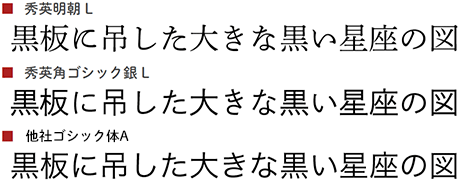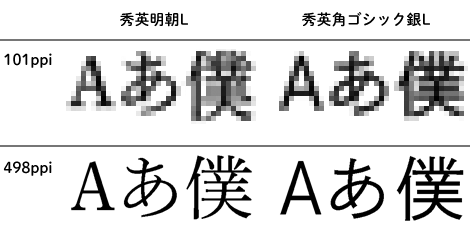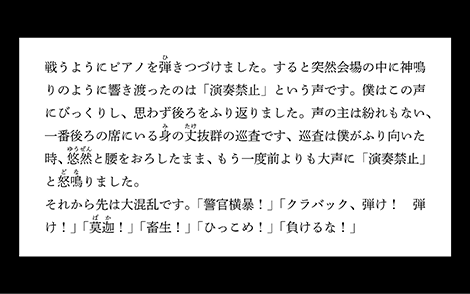
第38回 高精細ディスプレイなら明朝体が読みやすい!? ~読書速度の測定~
読みやすい書体とは?また、秀英体の「読みやすさ」は私たち担当者の思い込みでなく、読者の方に届いているでしょうか?
前回のコネタに引き続き、今回も書体の定量評価の取り組みをご紹介します。
紹介するのは、眼光学の専門家である北里大学の川守田先生(医療衛生学部准教授)と、ディスプレイメーカーの(株)ジャパンディスプレイとの三者共同で取り組んだ読みやすさの評価実験です。
どんな実験?
スマートフォンやタブレットPCなど、高精細化が進む液晶ディスプレイ。
ディスプレイの高精細化で文章は読みやすくなるか、書体の種類(明朝体とゴシック体)はディスプレイでの読みやすさに影響するかを評価しました。
比較する条件はディスプレイ精細度・書体・文字サイズです。ディスプレイの精細度は一般的なパソコンと同程度の101ppi(pixel per inch)から、高精細なスマートフォン(※1)と同程度の498ppiまでの4段階。書体は秀英明朝Lと秀英角ゴシック銀L、そして、一部のディスプレイに採用されている他社ゴシック体Aの3書体。文字サイズを3ptから10ptまでの5段階としました。
(※1 例えば、iPad Airは264ppi、iPhone 6s Plusは401ppi です。)
評価した3書体
今回の実験は、読書速度を「読みやすさ」の尺度としました。
200文字ほどの横組の文章を、条件(精細度・書体・文字サイズ)を変えてディスプレイに表示。実験参加者に黙読してもらい、読了時間を測定、読書速度(1秒あたりに読んだ文字数)を求めました。実験参加者は矯正視力1.2以上の大学生15名です。
評価用画像の例(秀英明朝L,10pt)
文章は「河童」(芥川龍之介)から用いました。同じ文章の繰り返しだと学習してしまうため、条件ごとに用いる文章を変えています。
高精細ディスプレイならゴシック体より明朝体が読みやすい!?
従来、印刷物には明朝体、ディスプレイ表示にはゴシック体が主に用いられてきました。実験前は、ディスプレイには明朝体は不向きかと考えましたが、精細度や文字サイズによっては、予想を覆す結果が出ました。
グラフ1:ディスプレイ精細度101ppiの読書速度(書体別プロット)
このグラフの縦軸は読書速度(1秒あたりに読んだ文字数)です。上にプロットされるほど速く、読みやすかったと考えられます。
101ppiでの書体別の読書速度を比較すると、5~7ptの文字サイズでは、秀英明朝Lはゴシック体の2書体に比べて遅く、読みにくいことが分かります。しかし、秀英明朝Lは、8~9ptでは他社ゴシック体Aと秀英角ゴシック銀Lとの中間の速度になり、10ptではゴシック体2書体よりも速い結果となりました。
グラフ2:ディスプレイ精細度498ppiの読書速度(書体別プロット)
一方、498ppiで比較すると、7pt以上の文字サイズで秀英明朝Lがゴシック体を2書体とも逆転し、読みやすいという結果になりました。9ptでは1秒あたり1文字の差が出ていますが、1時間で3600文字(およそ小説5ページ分)と考えると、この差は小さくないですよね!
ディスプレイの高精細化で読みやすさが向上!
書体別のグラフ3も見てみましょう。
秀英明朝Lは、ディスプレイ精細度や文字サイズによって、大きく速度差が出ています。一方、ゴシック体の2書体は、いずれの影響も小さく、安定した読書速度です。
グラフ3:秀英明朝L/秀英角ゴシック銀L/他社ゴシック体Aの読書速度
(ディスプレイ精細度別プロット)
また、総じて、ディスプレイの高精細化で読書速度が向上することが見て取れます。スマートフォン等に500ppiを超える高精細ディスプレイが実用化されてきましたが、その精細度をもってしても、日本語の読みやすさはまだ限界ではないのかもしれません。
まとめ(印刷物に近づくディスプレイの精細度がもたらすもの)
10ptにおける101ppi/498ppiのドット密度のイメージ
これは、10ptにおける秀英明朝L・秀英角ゴシック銀Lの、101ppi・498ppiのドット表示を拡大したイメージです。
101ppiでは1文字あたりのドットが粗い(約14pixel)ですが、明朝体と比べ、ゴシック体はデザインがシンプルなため、ぼやけても文字のシルエットが分かります。これが、従来のディスプレイでゴシック体が多用されてきた要因の1つでしょう。一方、498ppiでは1文字あたりのドットが密(約69pixel)で、複雑な漢字の形状や、画線のメリハリなど書体の特徴もつぶれずに表示できます。
今回の実験では、精細度が高まれば、明朝体がゴシック体より読みやすくなるという結果が出ました。高精細ディスプレイであれば、書体の特徴が活きることで、印刷物(※2)と同じように、明朝体が読みやすくなったのだと考えられます。
(※2 印刷物は600~1200dpi(dot per inch)が一般的です。)
補足 書体の特徴(可読性と視認性)
ゴシック2書体の読書速度の差から考察しました。
今回の実験結果が示すように、高精細化が進んだディスプレイでは、書体の微妙なニュアンスが表現できます。
これからは、印刷物と同じように、使う場面や目的によって特徴を意識した書体の選択が重要になってきます。電子書籍やウェブのコラムなど、読み物のコンテンツには、秀英体を選択肢の一つとしてご検討ください。